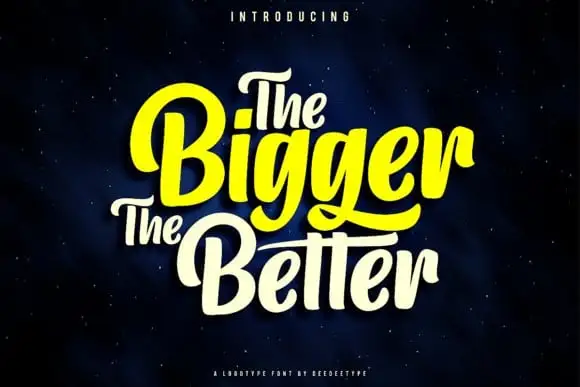
The Bigger The Better Script Font – Download Grátis
A fonte “The Bigger The Better Script Font” é uma escolha perfeita para designers que buscam criar mensagens criativas com estilo autêntico e moderno. Desenvolvida pela equipe de design de 99designs, essa letra cursiva moderna e chamativa traz seu próprio toque único a qualquer projeto gráfico. Com um design limpo e um ar um pouco engraçado, esta fonte é ideal para logotipos, marcas, redes sociais e projetos DIY criativos. Se você está procurando uma letra cursiva que possa dar ao seu trabalho um toque único de personalidade moderna e inovadora, “The Bigger The Better Script Font” é uma escolha ótima.